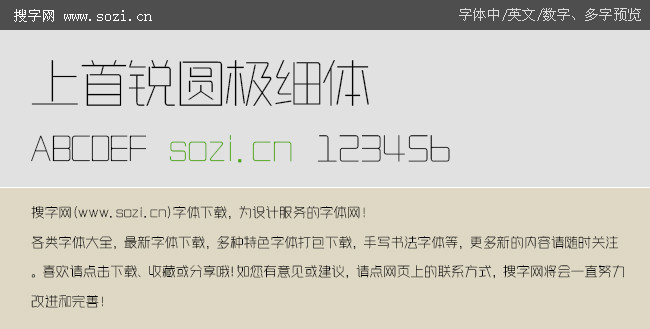
上首銳圓極細(xì)體
搜字網(wǎng)給大家提供一款上首銳圓極細(xì)體中文字體下載,上首銳圓極細(xì)體整體特征呈方圓形,筆畫粗細(xì)勻稱,字體下方轉(zhuǎn)角處作圓角處理,字體辨識(shí)度高,筆畫圓潤(rùn)流暢,看上去軟萌可愛,帶著幾分童趣,沒有攻擊性,給人舒適隨和的感覺?蓱(yīng)用于各類報(bào)紙、雜志、廣告等正文設(shè)計(jì)。